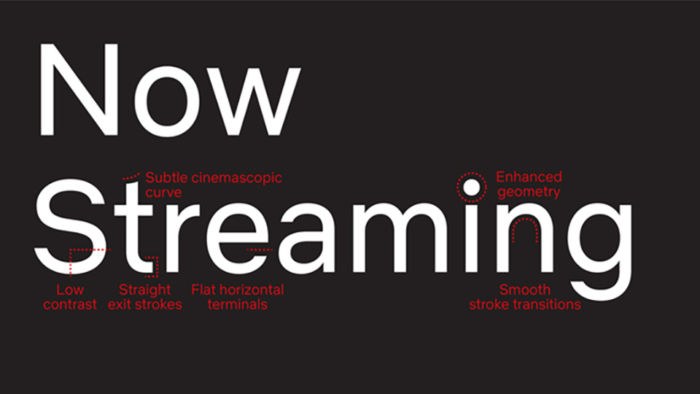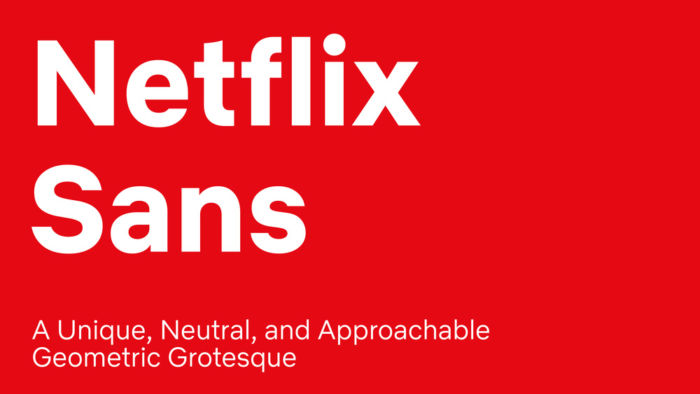
Netflix Sans, es el nombre que recibe la nueva tipografía personalizada de Netflix y que ha sido creada para implementarse en corto plazo en la marca en general; es decir, todo lo que tenga Netflix usará esta tipografía tal con lo ha implementado Coca-Cola tras el lanzamiento de Unity.
Cabe señalar que el lanzamiento de esta obedece a una creciente tendencia de las marcas de crear su propia apariencia personalizada, a la vez que ahorran miles de dolares al usar su propia tipografía para dar aspecto a su propia marca.
Tipografía personalizada de Netflix
Netflix Sans está diseñada para dar toque más cinemáticas a las mayúsculas que conforman la palabra Netflix; claro, de igual manera a las minúsculas; para que estas sean más compactas y eficientes; esta tipografía ha sido desarrollada por Noah Nathan y un equipo de profesionales que han dado en clavo para lograr un estética impecable en el branding de Netflix.